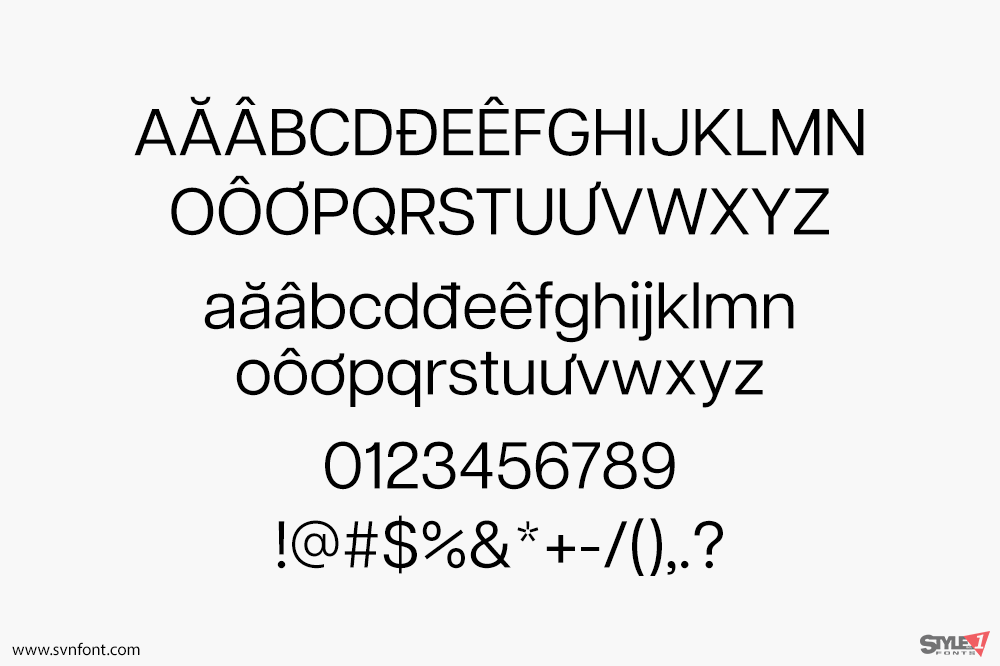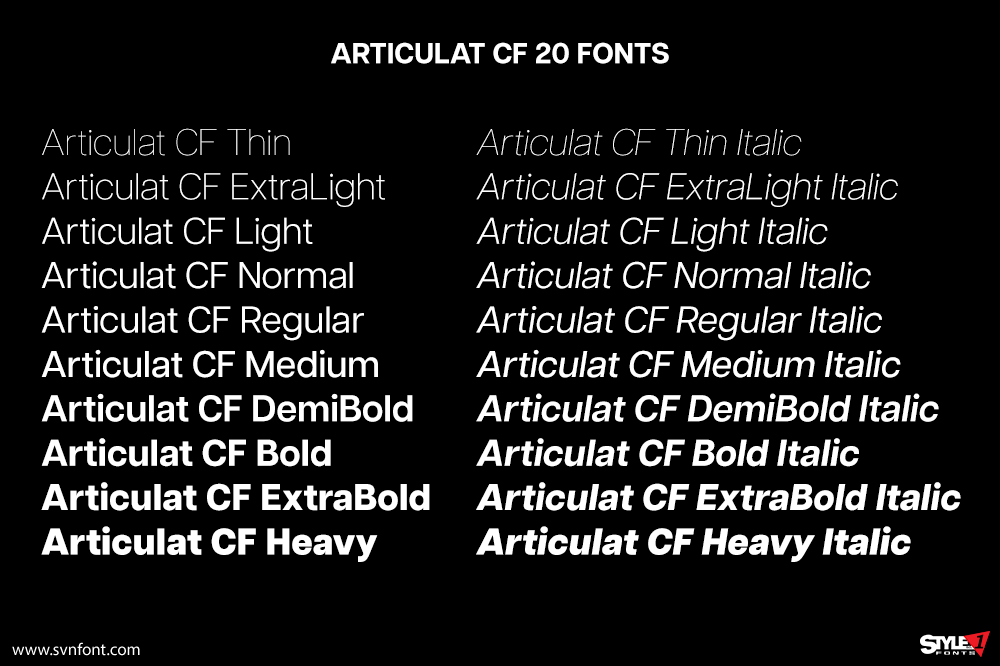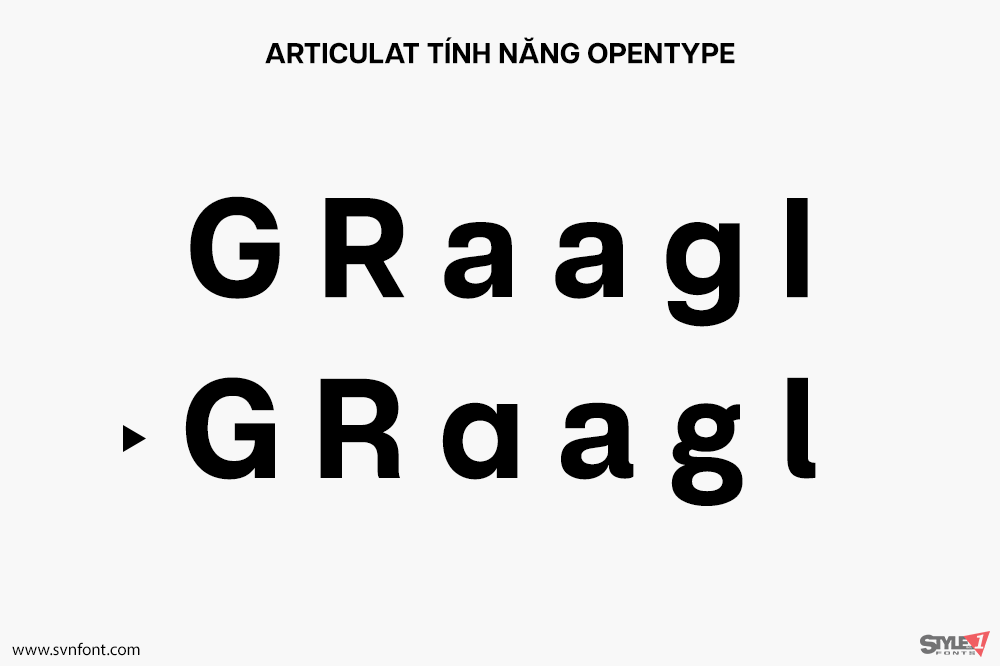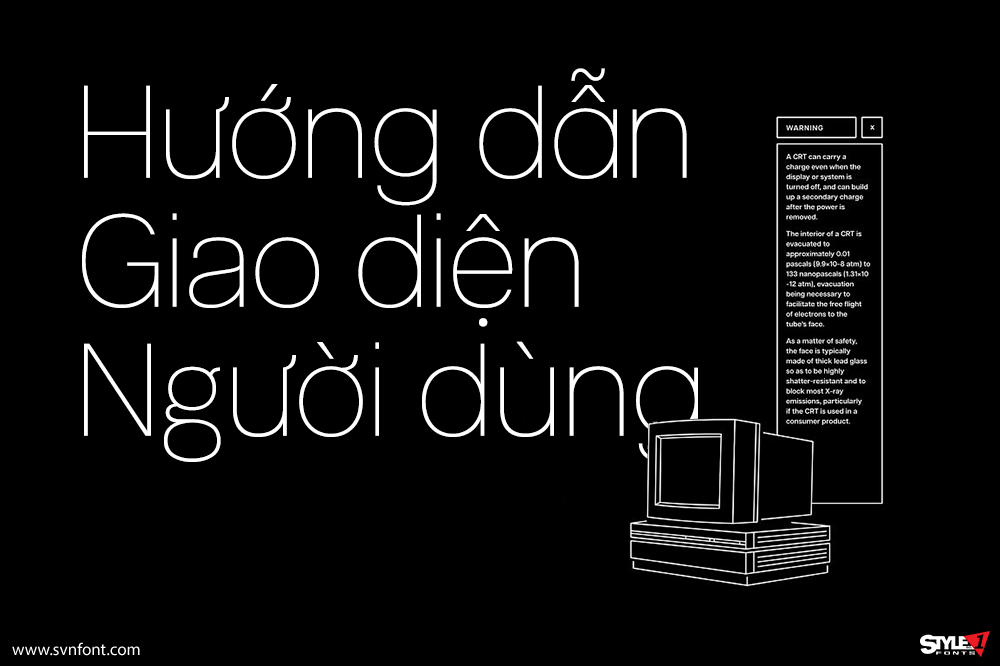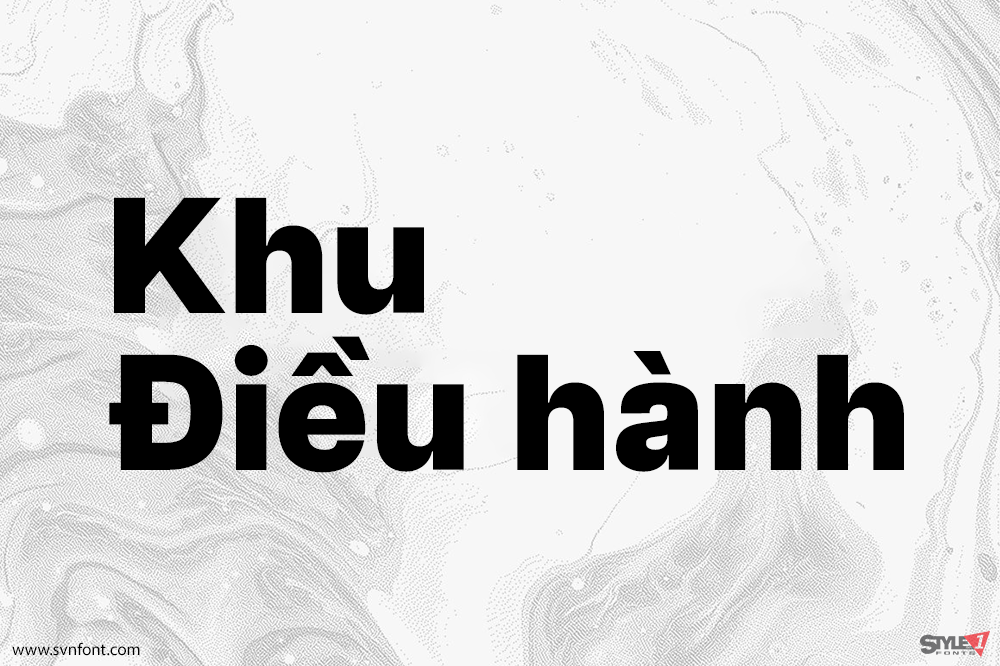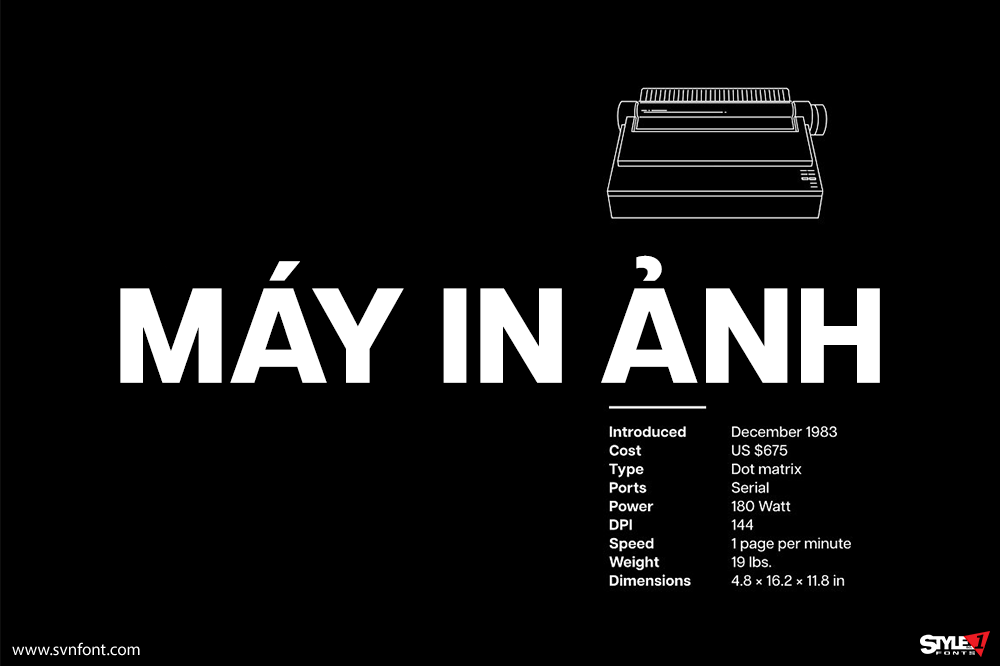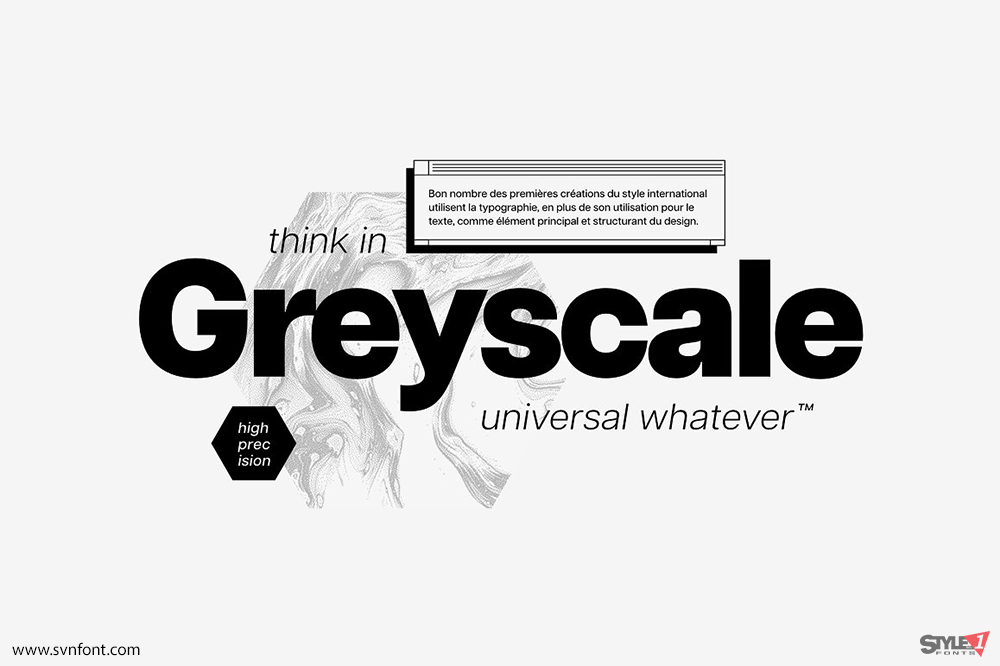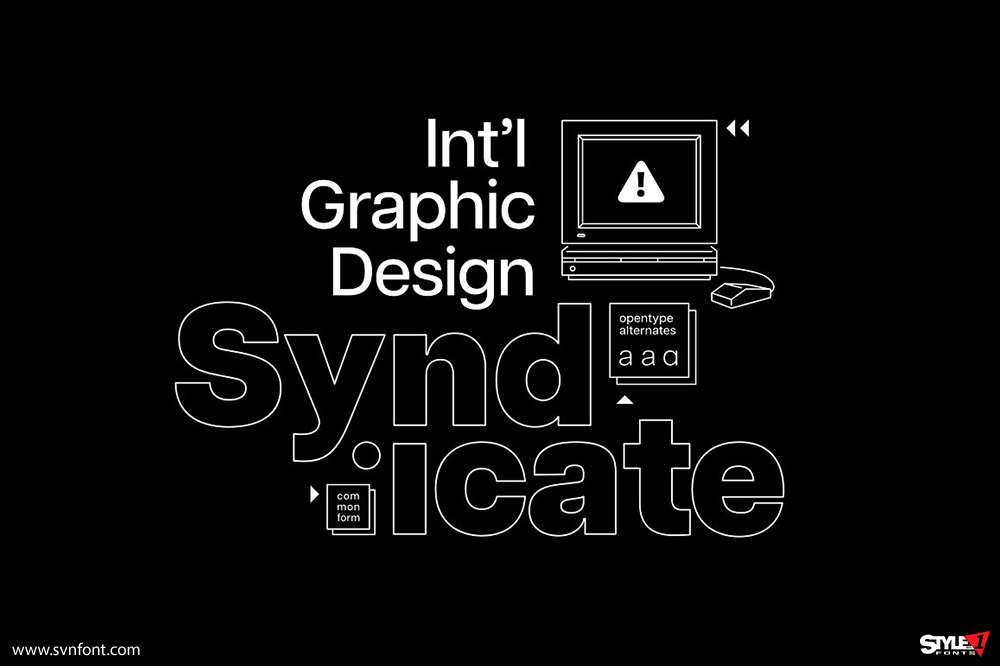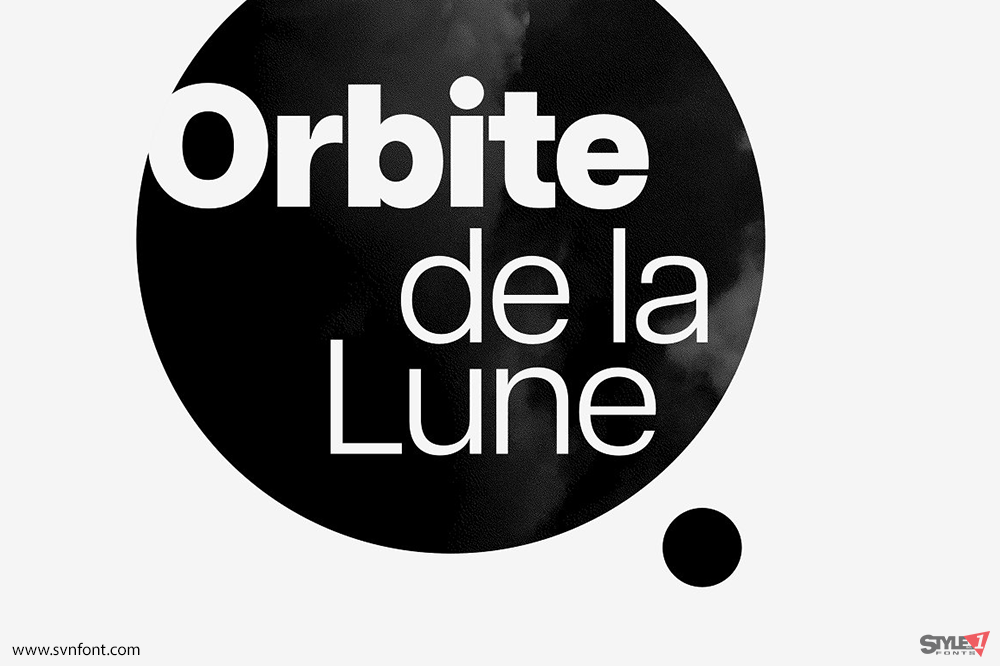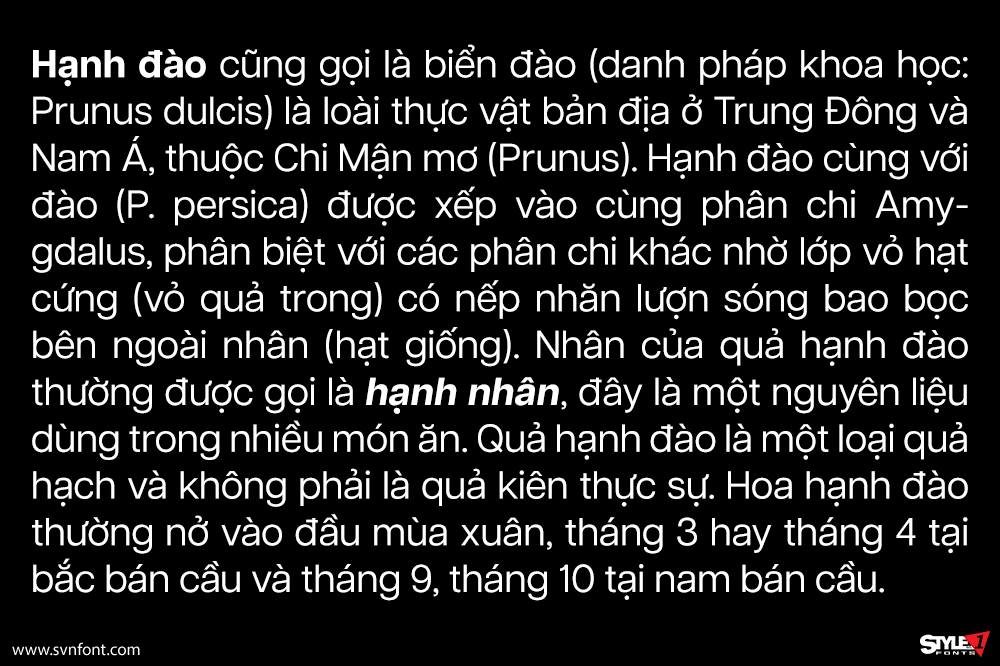
Articulat CF là một phiên bản tinh giản, cập nhật của thiết kế kiểu chữ giữa thế kỷ. Mạnh mẽ, sắc nét và rõ ràng, Articulat được xây dựng từ đầu với mục đích trở nên táo bạo, sạch sẽ và sáng sủa. Phiên bản 3 là một bản cập nhật lớn với hàng chục cải tiến. Mọi ký tự đều đã được xử lý để cải thiện đáng kể nhịp điệu và sự cân bằng, cùng với việc sửa các lỗi chung và chỉnh sửa kerning.
Nhà thiết kế: Connary Fagen
Nhà phát hành: Connary Fagen